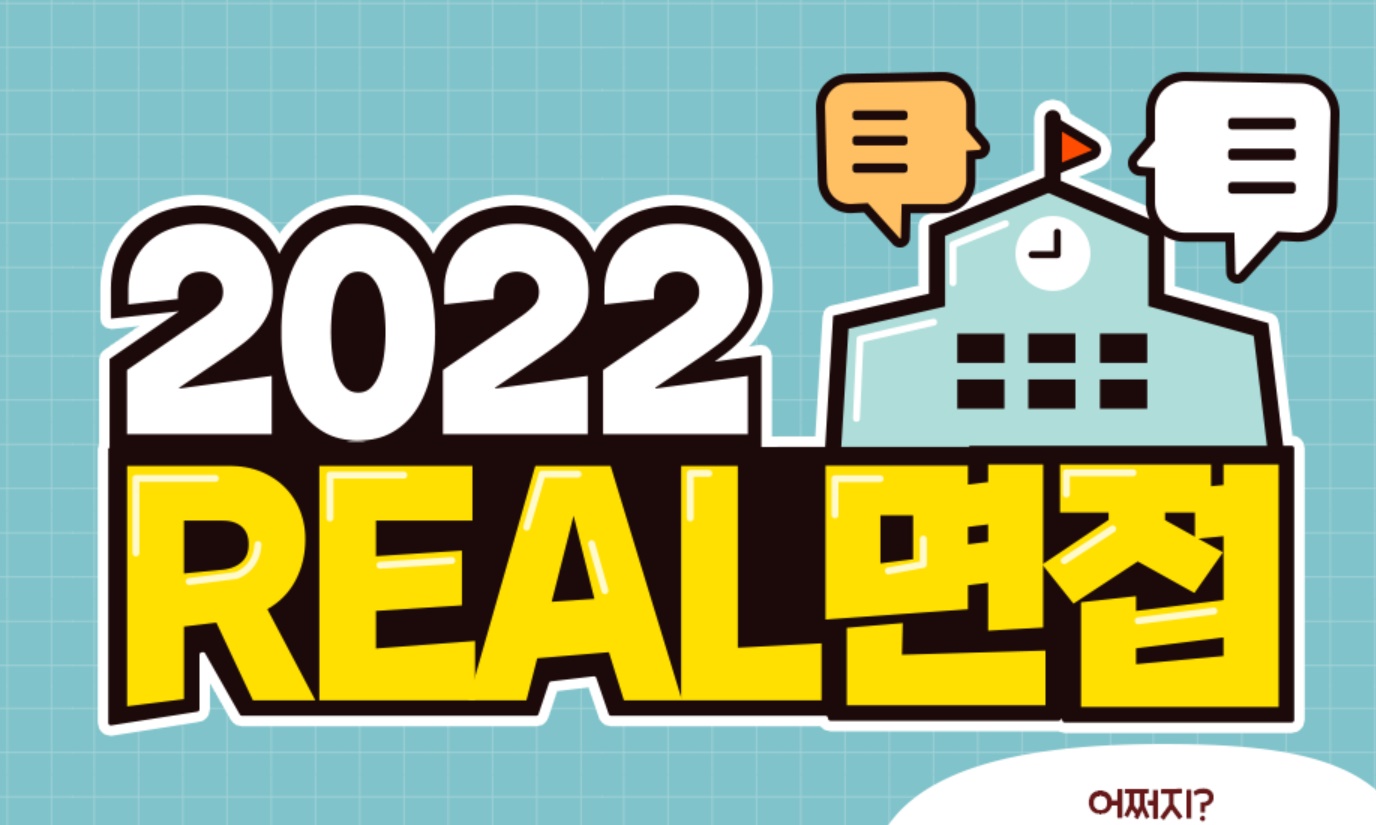
폰트가 궁금합니다 whr*** 2023.04.24 자음이 살짝비뚤어져서 디자인되어있는 폰트인데 궁금합니다 댓글 0 등록 sta*** Rix열정도체 같네요 https://www.sandollcloud.com/font/16501.html 2023-04-24 답글 달기 whr*** 감사합니다!! 2023-04-25 답글 달기 댓글 더보기 쉽고 빠르게 가장 비슷한 폰트를 알고 싶다면? 이미지로 검색하기
Rix열정도체 같네요 https://www.sandollcloud.com/font/16501.html